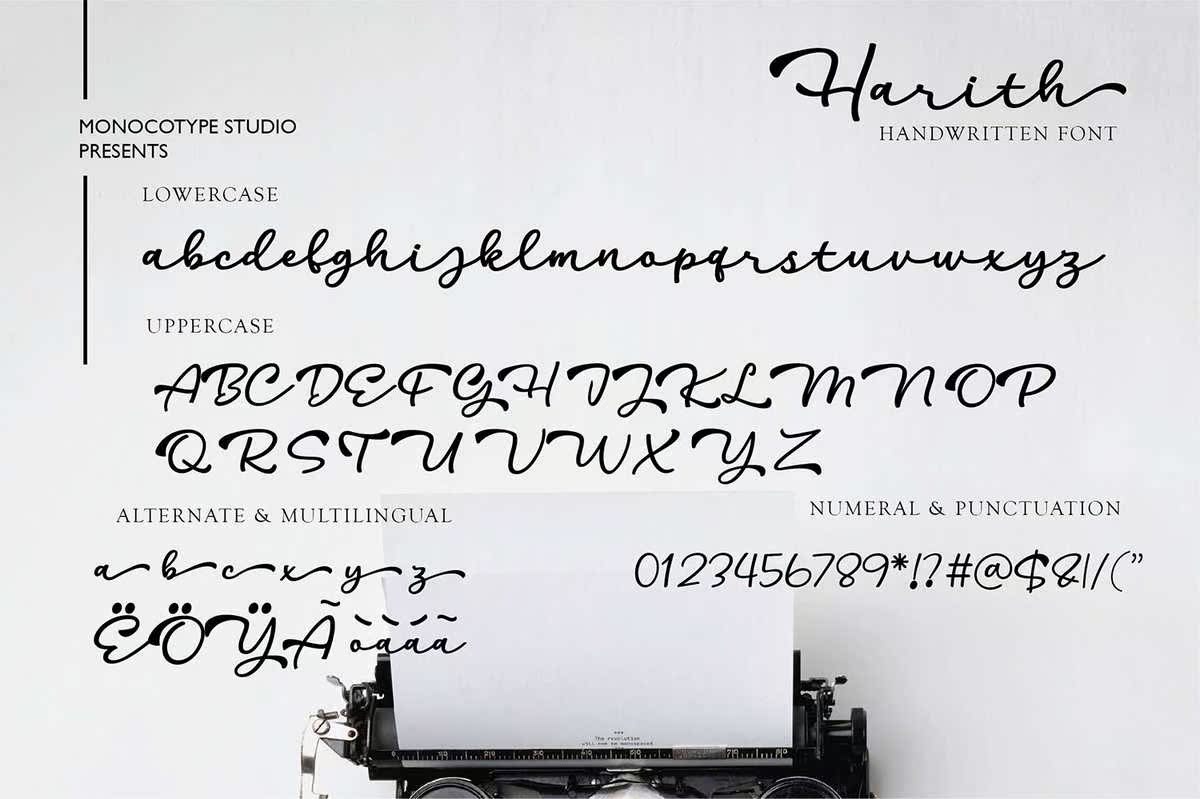
哈里斯这是一个描述,它在给人一种异国情调和流动印象的内文中被洗过。它可以用于不同的目的:文字和日志类型、标签、t恤、产品包装、邀请函、,广告和广告文字标识。这是一种描述内容,它在给人以异国情调和流畅印象的内文中出现。它可用于不同的目的:文字和日志类型、标签、t恤、产品包装、邀请函、广告和广告文字标识。